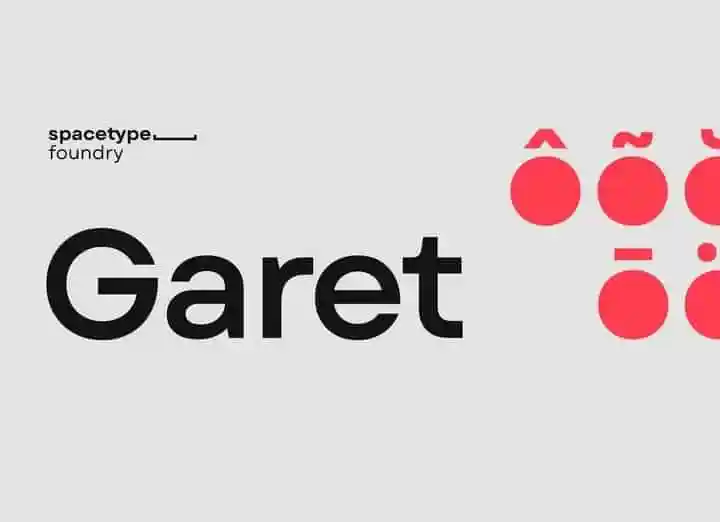
Garet Sans Serif Font – Fonte Grátis
Garet Sans Serif Font
A Garet Sans Serif é uma nova gótica tipográfica que surgiu dos geométricos padrões modernos. Desenhada por Mirela Belova e Stan Partalev, esta fonte contém formas com forte emoção contemporânea. O design de Garet se baseia em um conceito geométrico perfeito do círculo, cuja estética é mantida na forma dos seus detalhes, especialmente no formato oválico que dá à fonte sua identidade única. Além disso, sua disposição das áreas internas dos caracteres fechados contribui para a estética de um design moderno e amigável, combinando uma simplicidade elegante com uma força vibrante na tipografia. Se você está buscando uma fonte que não apenas atenda às necessidades da sua marca ou projeto gráfico, mas também adorne-o de maneira inovadora e arrojada, a Garet Sans Serif é uma excelente opção.